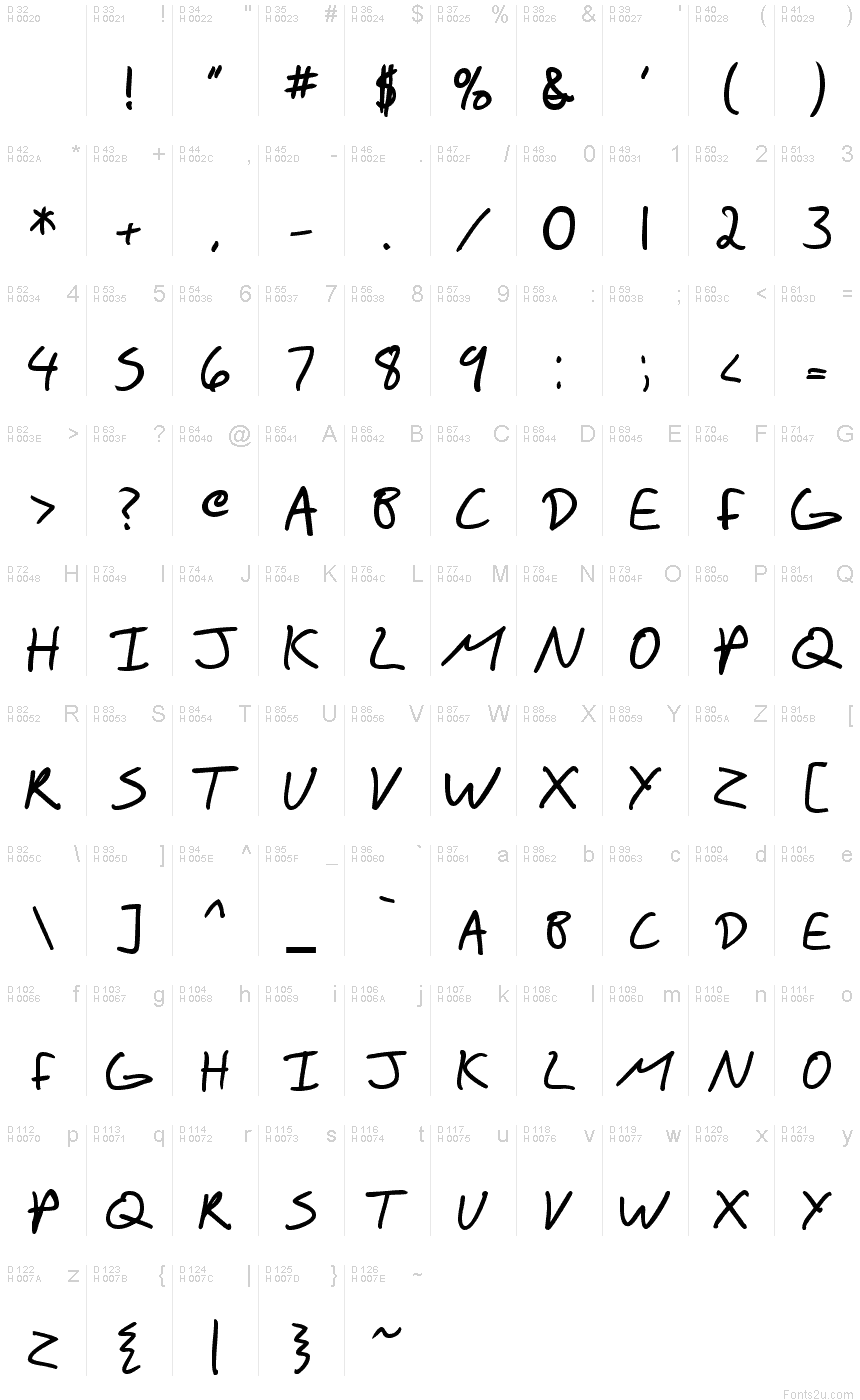
SF Scribbled Sans SC Bold od ShyFoundry to bezpłatny, odręczny krój bezszeryfowy, który oddaje luźny charakter szybkich notatek pisanych markerem. Pociągnięcia są szerokie i nierówne, z zaokrąglonymi łukami i otwartymi formami, co nadaje literom spontaniczny, surowy wygląd.
Ten darmowy font świetnie sprawdzi się w brandingu młodzieżowym, na okładkach zinów, nagłówkach plakatów, okładkach albumów i w zabawnych projektach opakowań, gdzie ta energia surowego pisma potrafi zdominować cały układ. Działa również dobrze w przypadku tytułów i krótkich cytatów, ponieważ szkicowe litery wnoszą natychmiastowe wrażenie ręcznej pracy, nie wpadając przy tym w przesłodzony styl skryptowy.
SF Scribbled Sans SC
ShyFoundry
Derek Vogelpohl